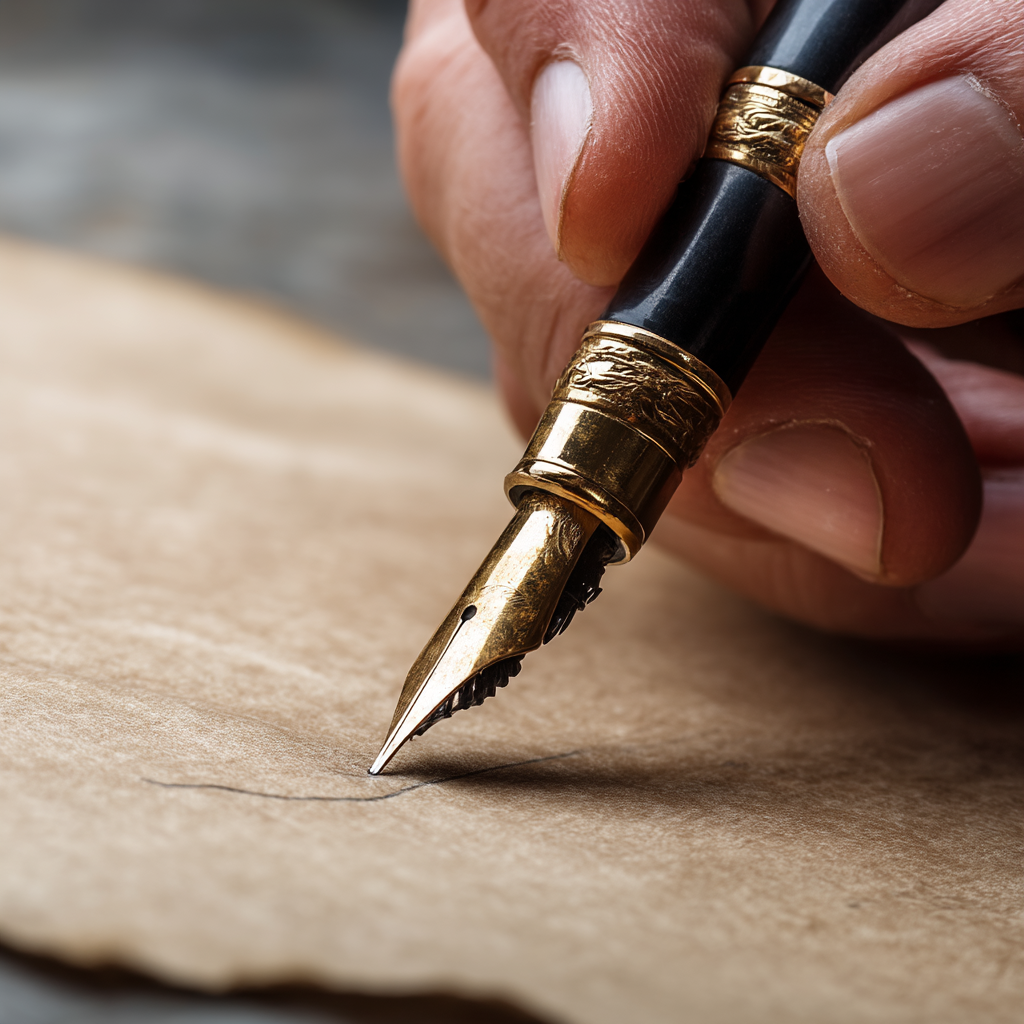
악필 탈출! 하루 10분 글씨 교정 루틴 글씨가 예쁘면 인상이 달라진다고 하잖아요? 그래서 많은 분들이 글씨 교정에 관심을 가지지만, 막상 시작하려면 막막한 경우가 많아요. ‘손이 굳어서 안 돼요’ 혹은 ‘시간이 없어요’라는 고민도 자주 들리죠. 그래서 준비했어요. 하루 딱 10분! 누구나 따라할 수 있는 간단한 글씨 교정 루틴을 공개할게요 😊
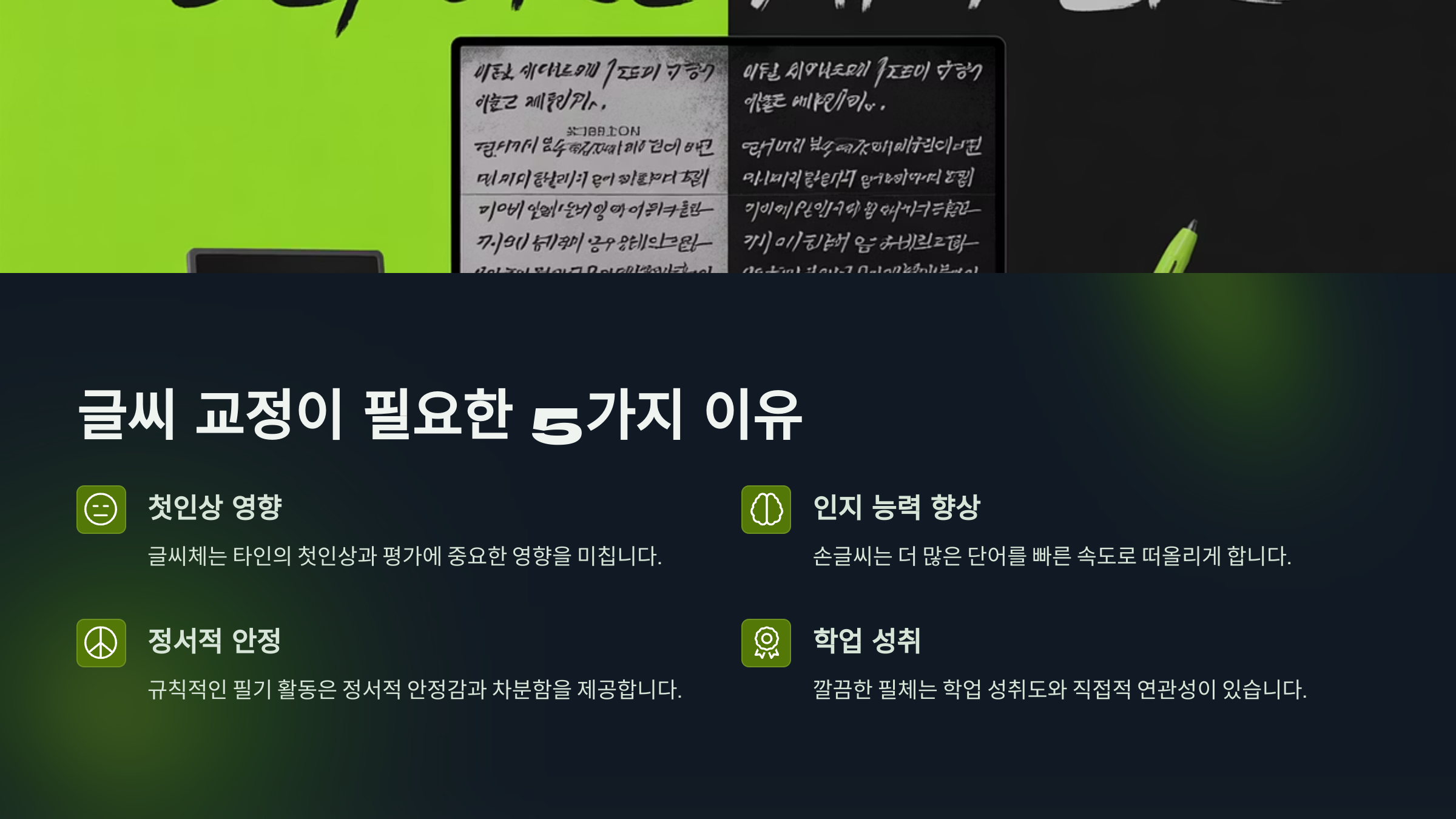
글씨 교정이 필요한 5가지 이유 이 루틴은 단순히 예쁘게 쓰는 법을 넘어, 손의 움직임과 감각을 되살리는 데 초점을 맞췄어요. 필압, 획의 시작과 끝, 자간, 행간 등 기본부터 차근차근 익힐 수 있도록 구성되어 있답니다. 매일 10분만 투자하면 악필에서 벗어나는 건 물론, 자신감도 쑥쑥 자라나게 될 거예요!
🧠 글씨 교정의 필요성과 심리
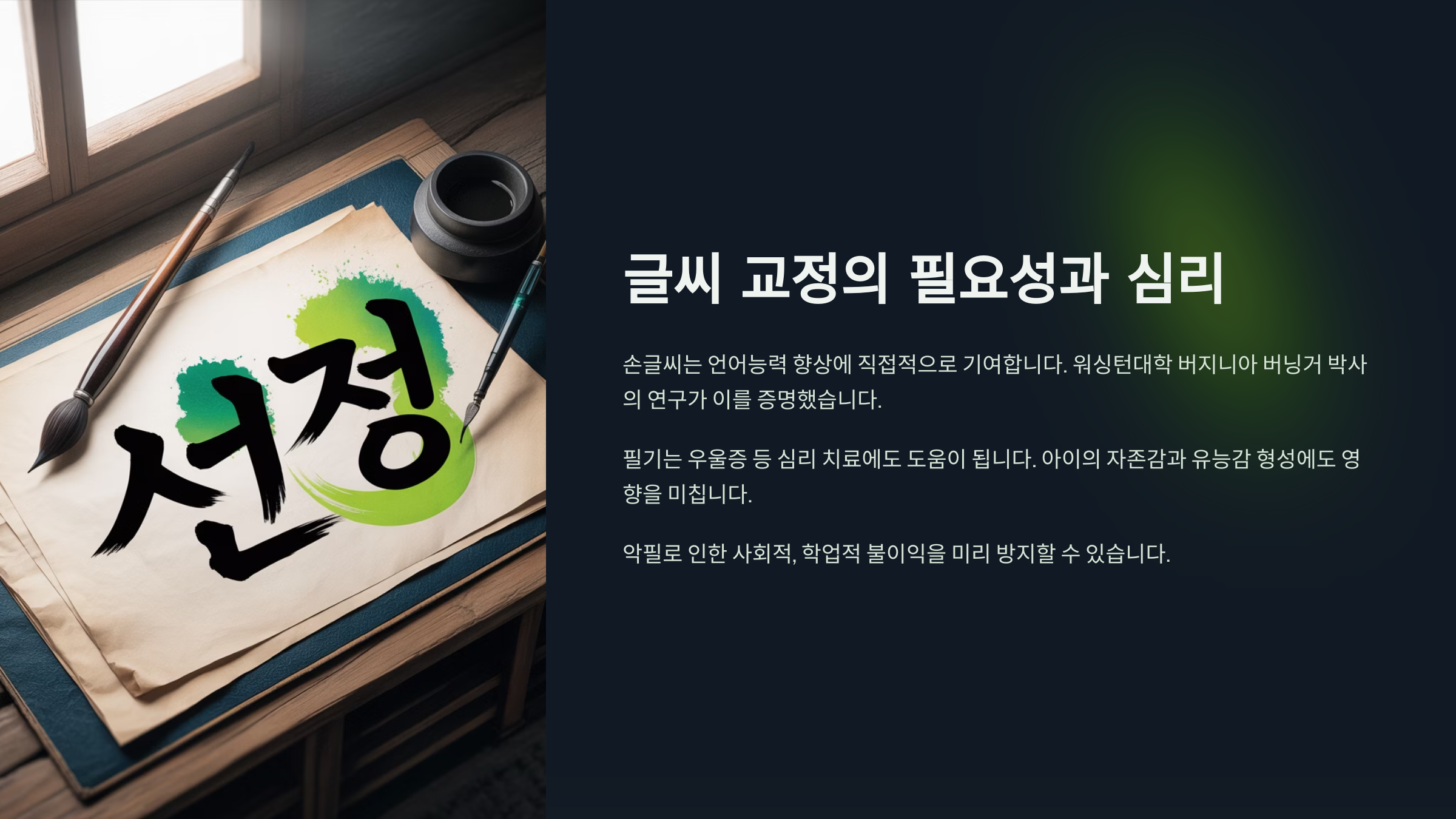
글씨 교정의 필요성과 심리
글씨가 곧 사람의 첫인상이라는 말, 들어본 적 있죠? 특히 메모나 카드, 신청서, 수기 문서처럼 손글씨가 여전히 필요한 상황에선 그 사람의 이미지까지 좌우하곤 해요. 글씨가 삐뚤빼뚤하거나 일관성이 없으면 부주의하거나 급해 보이는 인상을 줄 수 있어요.심리학적으로도 악필은 자신감 부족이나 긴장, 스트레스와 연결되는 경우가 많대요. 반대로 글씨가 또박또박해지면 자신감도 덩달아 높아지고, 집중력까지 향상된다는 연구 결과도 있답니다. 글씨를 바꾸면 생각과 감정까지 긍정적으로 바뀌는 셈이에요 😊
‘나는 원래 악필이야’라고 단정 짓기보단, 의식적인 훈련을 통해 누구나 글씨체를 바꿀 수 있어요. 제어된 반복을 통해 근육 기억을 되살리는 게 핵심이랍니다. 일상 속 작은 실천이 큰 변화를 만들어주는 거예요!
내가 생각했을 때, 글씨는 단순히 시각적인 결과물이 아니라, 나 자신을 표현하는 방식 중 하나라고 느껴져요. 그렇기 때문에 내 글씨가 나를 더 잘 보여줄 수 있도록 노력하는 건 꽤 의미 있는 일인 것 같아요 🖋
📊 글씨 교정이 심리에 미치는 영향
영역 변화 설명 자신감 상승 글씨체 개선은 자신에 대한 믿음을 높여줘요. 집중력 향상 획에 집중하며 쓰는 과정이 집중력을 키워줘요. 자기표현 강화 또박또박한 글씨는 자기 표현력에 영향을 줘요. 손글씨는 그 사람의 내면을 드러내는 도구이기도 해요. 같은 문장이라도 누가 쓰느냐에 따라 전혀 다른 느낌을 주니까요. 글씨를 바꾸려는 마음가짐은 나를 새롭게 재정비하는 첫걸음이 될 수 있어요!
그런 이유로 요즘엔 ‘필사’나 ‘펜글씨 연습’이 감정 조절을 위한 힐링 활동으로도 주목받고 있어요. 집중해서 손글씨를 쓰는 동안 마음이 안정되고 불안도 줄어든다고 하니, 일석이조의 효과를 누릴 수 있답니다.
물론 처음엔 어색할 수 있어요. 하지만 계속 쓰다 보면 손에 익고, 어느 순간부터는 손이 먼저 반응하게 된답니다. 꾸준함이 가장 강력한 무기예요 💪
글씨 교정이 단순한 연습을 넘어서, 자기 성찰의 과정이자 긍정적인 루틴이 될 수 있다는 점, 꼭 기억해보세요. 멋진 손글씨는 결국 내면의 자신감에서부터 시작돼요!
⏰ 하루 10분 루틴의 핵심 원칙
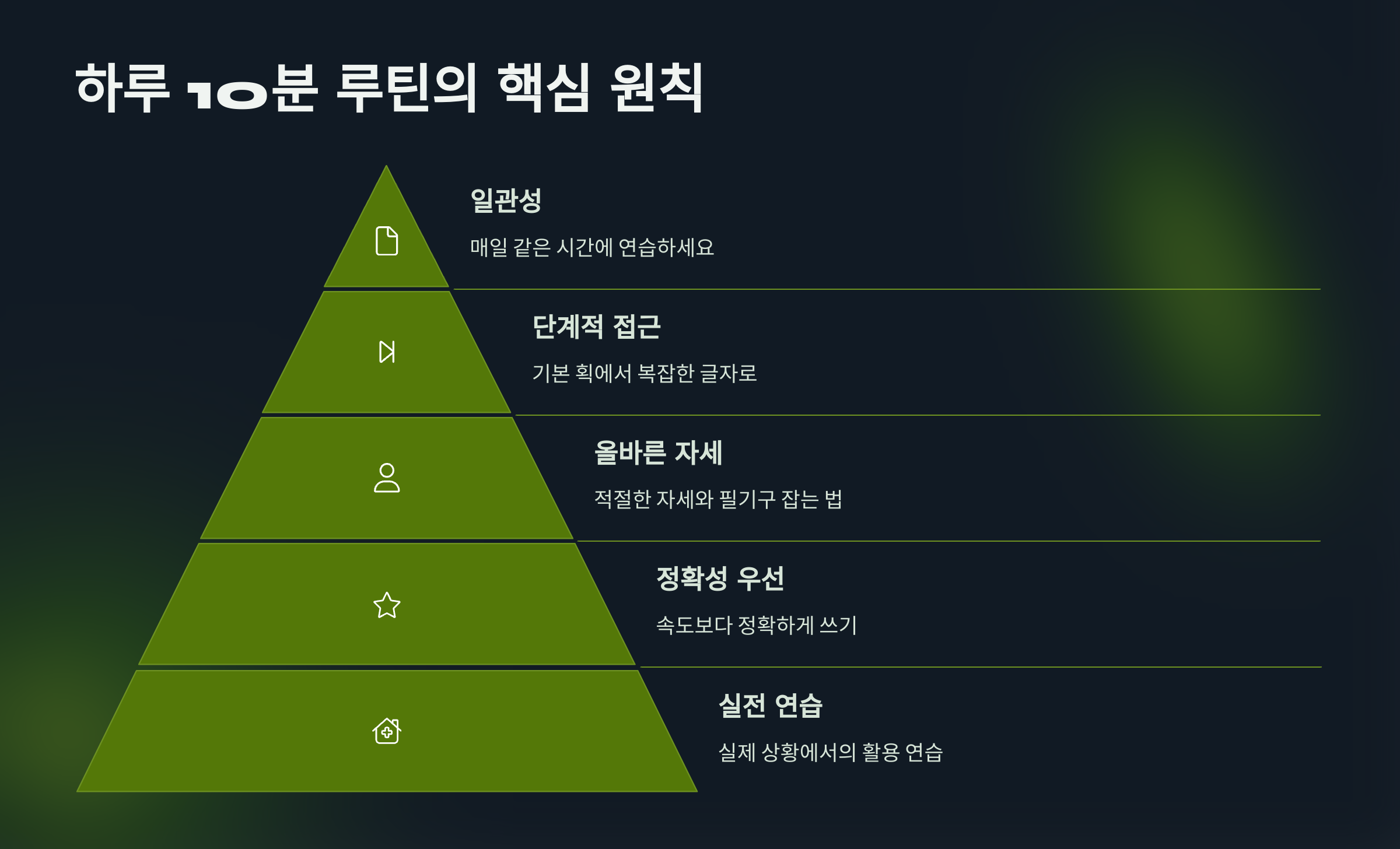
하루 10분 루틴의 핵심 원칙 글씨 교정에 필요한 시간은 사실 생각보다 짧아요. 하루에 단 10분만 투자해도 손의 움직임과 근육 기억을 충분히 자극할 수 있답니다. 중요한 건 그 시간을 얼마나 ‘집중해서’ 사용하느냐에 달려 있어요.
핵심은 ‘짧고 자주’. 한 번에 오래 쓰는 것보다, 매일 꾸준히 조금씩 연습하는 게 훨씬 효과적이에요. 뇌와 손의 연결을 지속적으로 훈련해야 진짜 내 글씨가 되니까요. 물 흐르듯 반복하는 것이 관건이랍니다.
또 하나 중요한 원칙은 ‘올바른 자세’. 글씨는 손끝에서 나오지만, 전체적인 자세가 흐트러지면 손에 힘이 제대로 전달되지 않아요. 바른 자세와 편안한 필기 환경을 만들어주는 것부터 시작해보세요 😊
연습할 때는 글자 하나하나에 ‘의식’을 담는 것이 좋아요. 아무 생각 없이 휘갈기기보다는, 획의 시작과 끝을 의식하면서 쓰면 훨씬 빠르게 개선된답니다. 이 과정을 통해 손글씨에 정성이 담기게 되어요.
🪄 루틴 성공을 위한 5가지 키포인트
원칙 설명 매일 10분 지속성 있는 반복이 가장 중요해요. 바른 자세 등은 세우고, 손목에 무리가 가지 않도록 해요. 획 연습 일직선, 곡선, 점 등 기본 획 연습이 핵심이에요. 의식적인 쓰기 생각하며 천천히 쓰는 게 훨씬 효과적이에요. 기록과 비교 진행 상황을 기록하면 동기부여가 생겨요. 이 다섯 가지 원칙만 잘 지켜도, 놀라울 정도로 글씨가 달라진답니다. 중요한 건 ‘완벽하게’가 아니라 ‘꾸준하게’라는 점! 너무 부담 갖지 말고 즐기는 마음으로 시작해보세요 😄
또한, 무리해서 필사량을 늘리기보다는 짧은 문장을 반복하는 것이 더 효과적이에요. 특히 익숙한 문장을 골라 감정을 담아 쓰면 글씨에 힘이 실리거든요.
자기 전에 10분, 혹은 아침 루틴에 포함시키는 것도 추천해요. 하루의 시작과 끝에 글씨를 쓰면 뇌와 손이 자연스럽게 리듬을 타게 된답니다.
이제 루틴의 핵심을 알았다면, 실제로 어떻게 구성하는지 궁금하시죠? 다음 섹션에서 바로 소개해드릴게요 ✨
📘 실제 루틴 구성 방법
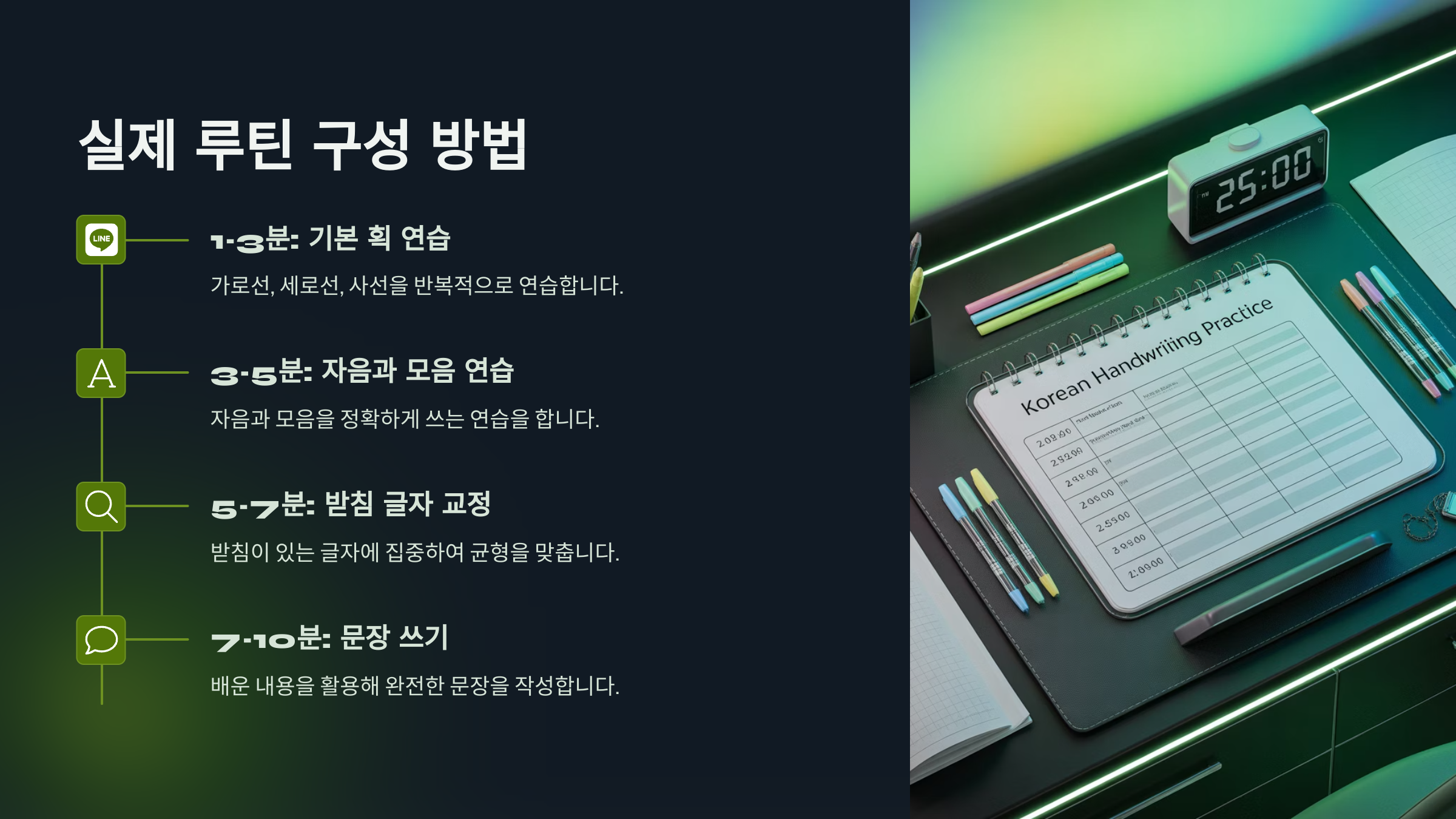
실제 루틴 구성 방법
실제 글씨 교정 루틴은 간단하지만 체계적으로 짜는 것이 중요해요. 여기선 아침 10분 루틴을 기준으로 설명드릴게요. 이 루틴은 초보자도 쉽게 따라할 수 있도록 설계되어 있어요.1분 준비 – 자세 잡기 & 필기도구 정렬
2분 기초 획 연습 – 세로선, 가로선, 점찍기
3분 단어 반복 – ‘감사’, ‘행복’, ‘기쁨’ 등 감성 단어 쓰기
3분 문장 연습 – 좋아하는 시구나 명언 필사
1분 체크 – 오늘 글씨에서 달라진 점 보기이렇게 구성하면 단순한 연습이 아닌, 감정과 마음까지 담긴 루틴이 돼요. 좋아하는 글귀를 반복해 쓰다 보면 글씨와 함께 하루의 감정도 정돈되는 느낌을 받을 수 있죠 ✨
매일 같은 문장을 쓰는 것도 좋지만, 주제를 바꿔보는 것도 좋아요. 예를 들어 월요일은 ‘희망’, 화요일은 ‘도전’ 같은 식으로 테마를 바꾸면 루틴이 지루해지지 않아요 😊
📑 루틴 구성 예시표
시간 활동 목적 1분 자세 정렬 & 준비 몸과 마음 집중하기 2분 기초 획 쓰기 선의 균형 & 필압 훈련 3분 단어 필사 단어 형태 익히기 3분 문장 필사 글씨 흐름 익히기 1분 글씨 피드백 자기 점검 & 변화 체감 이 루틴은 아침이나 점심, 자기 전 등 하루 중 어느 시간에 해도 효과는 같아요. 중요한 건 같은 시간, 같은 장소에서 반복하는 습관을 들이는 거예요. 습관이 되면 손이 먼저 반응하게 될 거예요 ✍
특히 루틴 중 마지막 ‘피드백’ 단계가 정말 중요해요. 작은 변화라도 놓치지 않고 적어보면 꾸준히 쓰고 싶은 마음이 생기거든요. 변화가 눈에 보일 때 성취감도 덩달아 커지니까요!
그럼 다음 박스에서는 글씨를 교정하는 데 도움이 되는 ‘필기 도구’에 대해 알아볼게요! 도구 하나만 바꿔도 결과가 확 달라진답니다 🖊
🖋 도움이 되는 필기 도구들
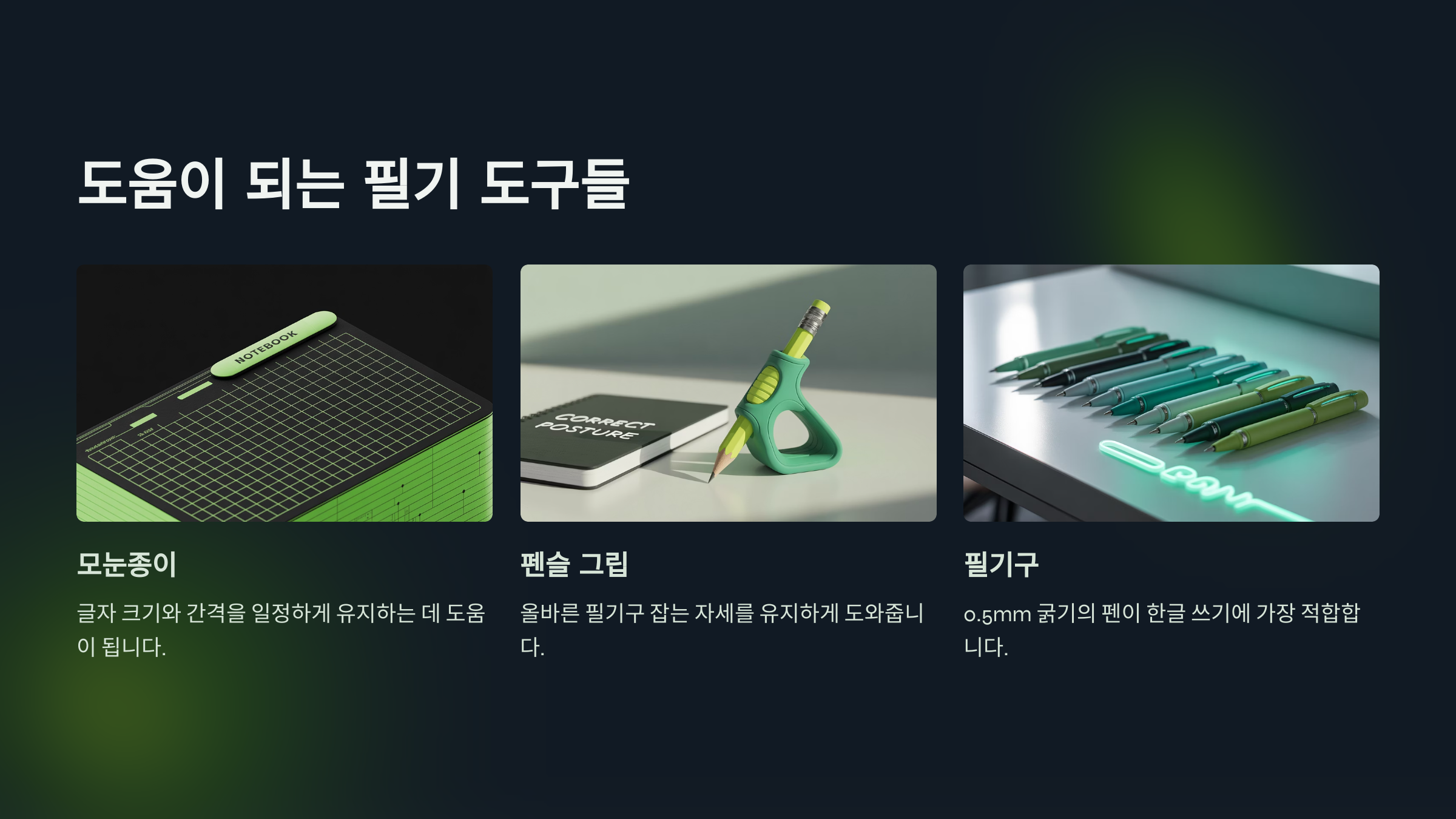
도움이 되는 필기 도구들
글씨 교정에 있어 ‘무엇으로 쓰느냐’는 생각보다 중요한 요소예요. 필기 도구가 손에 잘 맞아야 편안하게 쓸 수 있고, 그만큼 획도 안정적으로 나와요. 손에 부담이 적으면서도 제어하기 쉬운 도구를 고르는 게 핵심이죠!가장 추천되는 건 젤펜이나 저점도 볼펜이에요. 부드럽게 써지면서도 필압 조절이 쉬워서 획을 안정적으로 그릴 수 있답니다. 필기감도 좋고 번짐도 적어서 초보자에게 안성맞춤이에요.
연습 초반에는 연필을 사용하는 것도 좋아요. 특히 2B 정도의 부드러운 연필은 손의 떨림을 잡아주고 획의 흐름을 확인하기 쉬워요. 다만 너무 미끄럽거나 번지는 펜은 피하는 것이 좋아요!
노트 선택도 중요해요. 줄 간이 너무 촘촘하면 자간 조절이 어렵고, 너무 넓으면 글자 크기가 불안정해지죠. 6mm~7mm 간격의 라인노트가 가장 이상적이에요. 그리드 노트도 자형 익히기에 효과적이랍니다 📒
🛠 추천 필기 도구 비교표
도구 장점 단점 추천 여부 젤펜 부드러운 필기감, 명확한 획 잉크 양 많으면 번짐 👍 적극 추천 저점도 볼펜 정확한 제어 가능 힘이 들어가면 끊김 발생 ⭕ 추천 2B 연필 획의 연습에 최적 지워질 수 있음 🔄 초보자 추천 글씨 교정은 도구에 따라 흥미와 지속력도 좌우될 수 있어요. 나에게 맞는 펜 하나만 찾아도 쓰는 재미가 생기고, 루틴이 자연스럽게 이어진답니다 😄
도구를 고를 때는 문구점에서 실제로 테스트해보는 것도 추천해요. 손에 맞는 필기감은 사람마다 다르기 때문에 직접 써보는 게 제일 정확하죠!
그럼, 다음 섹션에서는 글씨를 교정하면서 흔히 저지르는 실수와 그 해결법을 알려드릴게요! 실수도 과정의 일부니까 걱정 말고 함께 살펴봐요 🔍
❌ 교정 시 흔한 실수와 해결법
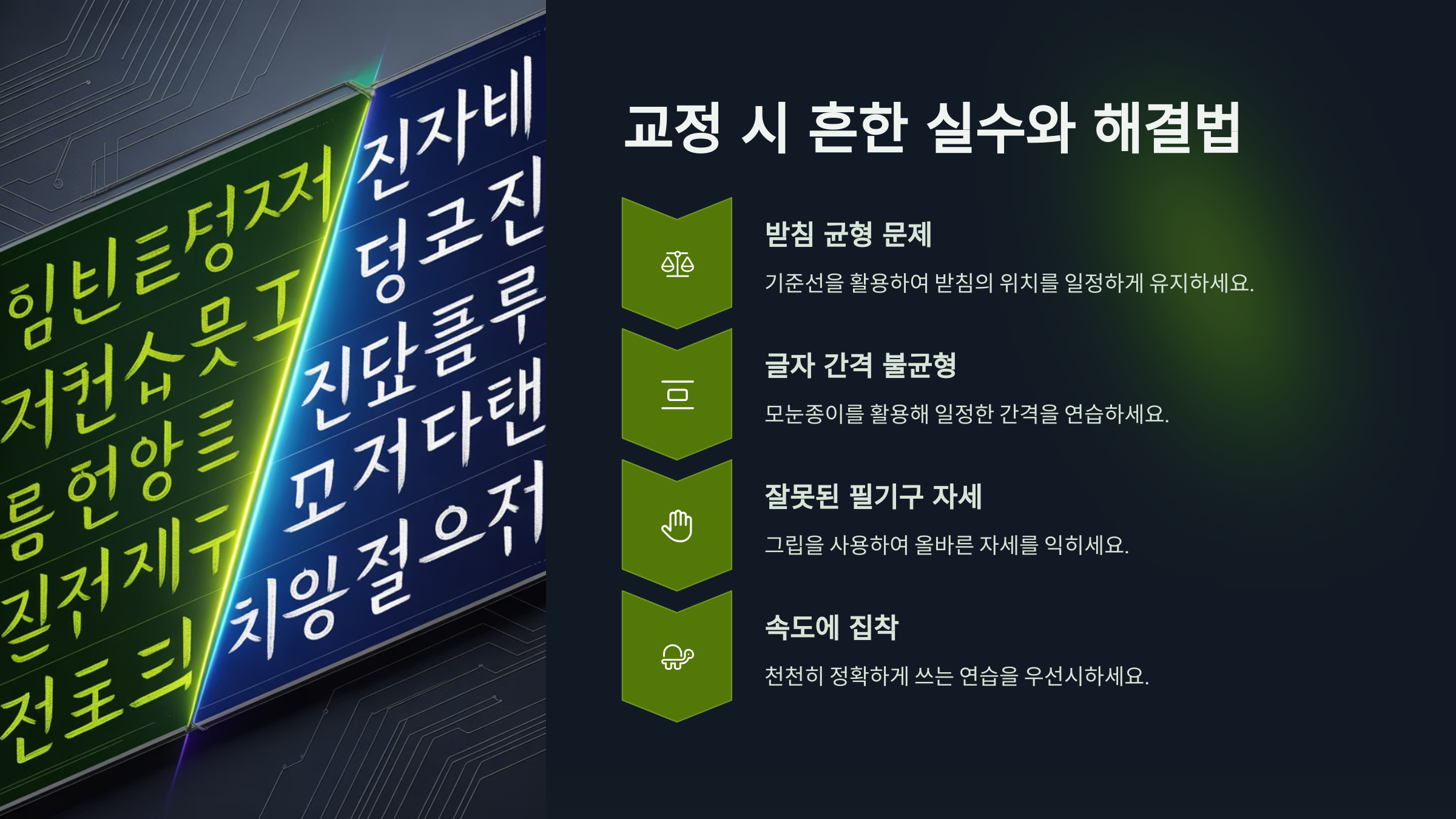
교정 시 흔한 실수와 해결법 글씨 교정은 반복적이고 지루할 수 있는 작업이지만, 실수도 교정 과정의 일부랍니다. 처음에는 흔히 저지르는 실수들이 있어요. 그런 실수들을 파악하고 고쳐나가는 게 중요해요!
첫 번째 실수는 ‘급하게 쓰는 것’이에요. 글씨는 시간과 마음을 들여서 써야 예쁘게 나옵니다. 서둘러 쓴 글씨는 획이 일관되지 않고, 형태가 흐트러지기 일쑤죠. 글씨를 쓸 때는 천천히, 신중하게 쓰는 것이 필요해요.
두 번째는 ‘자세가 불안정한 것’이에요. 책상에 앉아서 허리를 구부리고 쓰면 팔꿈치가 떠서 필압이 고르지 않아요. 바른 자세를 잡는 게 필기에서 중요한 포인트랍니다. 책상에 팔꿈치를 고정하고, 손목을 부드럽게 유지해 보세요.
세 번째 실수는 ‘글씨의 크기와 자간을 일정하게 유지하지 않는 것’이에요. 자간이 너무 좁거나 넓으면 글씨가 어지럽게 보일 수 있어요. 이를 해결하려면 ‘눈에 보이는 것보다 조금 더 넓게 쓰는’ 연습을 해보세요. 자간을 의식적으로 조정하면서 글씨를 써보면 개선된답니다 ✍
🧐 교정 시 자주 하는 실수 & 해결 방법
실수 해결법 급하게 쓰기 천천히, 신중하게 한 획씩 그리기 자세 불안정 팔꿈치 고정, 손목을 부드럽게 유지 자간 불규칙 의식적으로 자간을 일정하게 맞추기 이 실수들은 누구나 처음에 겪는 것들이에요. 하지만 이를 인식하고 수정하면 금방 글씨가 예뻐지고, 교정도 쉬워질 거예요! 조금만 인내심을 가지고 계속 연습하다 보면 점점 글씨에 자신감이 생길 거예요 😊
글씨를 고칠 때 가장 중요한 건 바로 ‘꾸준함’이에요. 하루 10분 루틴을 지속하면 점점 눈에 띄게 개선될 거랍니다. 실수도 반복하면서 고쳐가니까요! 글씨 교정은 한 번에 완벽하게 되는 게 아니라, 점진적으로 나아가는 과정이에요.
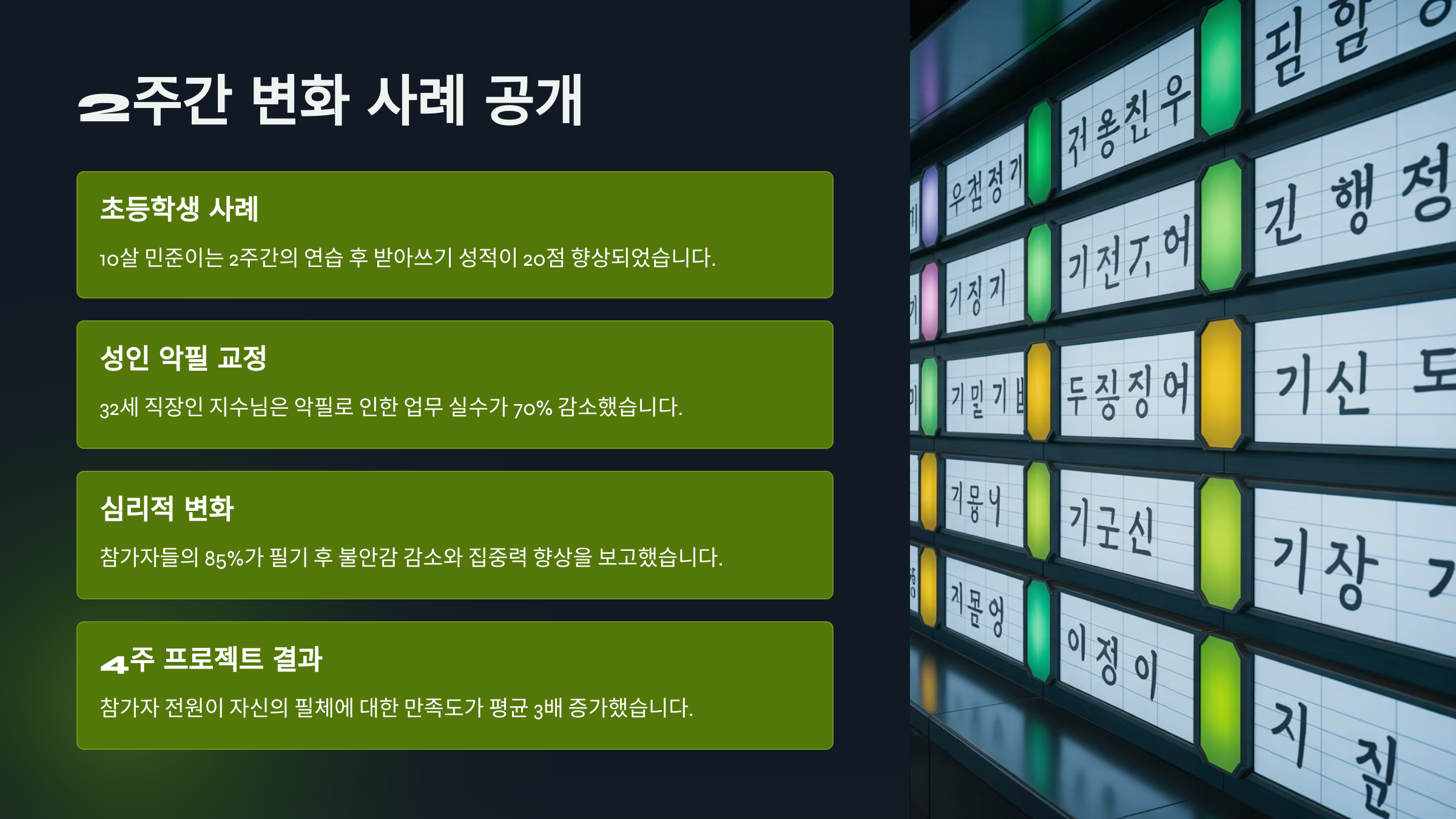
2주간 변화 사례 공개 📈 2주간 변화 사례 공개
자, 그럼 이제 2주간의 변화 과정을 공개할게요! 하루 10분씩만 투자해도 정말 많은 변화가 있어요. 아래 사례를 통해 변화 과정을 함께 살펴보세요.
첫 주에는 손의 움직임을 정확히 조절하는 데 집중했어요. 획을 일정하게 만들고, 글자 크기와 자간을 맞추기 위해 신경을 썼죠. 그 결과, 글씨가 조금 더 일정해졌고, 일관된 느낌이 들었어요. 두 번째 주에는 자세를 더욱 신경 써서 글씨의 안정감을 확실히 느낄 수 있었답니다.
2주 후에는 무엇보다 ‘자신감’을 느낄 수 있었어요. 예전엔 손글씨가 조금 부끄럽고 불안정한 느낌이었는데, 이제는 깔끔하고 안정적인 글씨를 쓸 수 있게 됐어요. 꾸준히 연습하다 보니 손이 자연스럽게 움직여지더라고요!
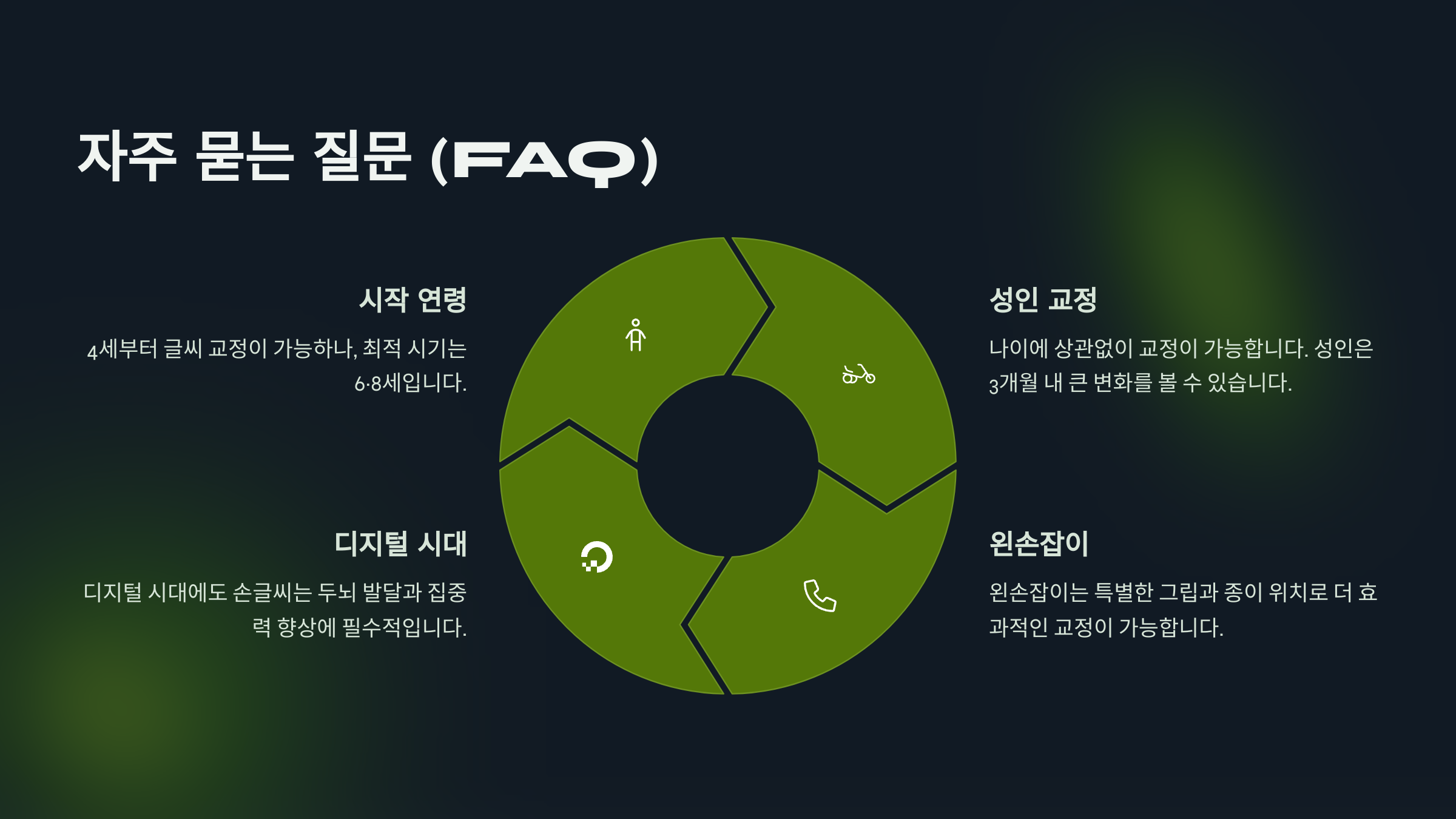
Q1. 글씨 교정은 정말 효과가 있나요?A1. 네, 꾸준히 연습하면 확실히 효과가 있어요. 글씨 교정은 손의 근육 기억을 개선하고, 자신감을 높여줍니다. 특히 2주 정도 꾸준히 하다 보면 눈에 띄는 변화를 느낄 수 있어요!
Q2. 하루 10분만 하면 충분한가요?
A2. 네, 하루 10분이라도 꾸준히 한다면 충분히 효과를 볼 수 있어요. 중요한 건 시간을 정해 놓고 매일 꾸준히 연습하는 것이랍니다.
Q3. 글씨 교정을 할 때 어떤 도구를 써야 하나요?
A3. 젤펜이나 저점도 볼펜이 추천돼요. 필기감이 부드러워서 제어가 쉬운 도구를 사용하면 글씨가 훨씬 안정적으로 써져요.
Q4. 글씨가 예쁘지 않으면 어떻게 해야 하나요?
A4. 처음에는 누구나 글씨가 마음대로 되지 않아요. 중요한 건 꾸준히 연습하면서 조금씩 개선하는 거예요. 너무 빨리 포기하지 말고, 한 걸음씩 나아가면 좋아요!
Q5. 교정할 때 자주 하는 실수가 무엇인가요?
A5. 급하게 쓰거나 자세가 불안정한 경우가 많아요. 이럴 때는 천천히 글씨를 써보거나, 바른 자세를 유지하며 필기하는 것이 좋아요.
Q6. 글씨 교정을 할 때 필기구는 계속 바꿔야 하나요?
A6. 아니요, 일관되게 사용하는 것이 중요해요. 일단 자신에게 맞는 필기구를 찾은 후에는 그 도구로 꾸준히 연습하는 것이 더 효과적이에요.
Q7. 글씨를 개선하면 심리적으로 변화가 있나요?
A7. 네, 글씨를 개선하면 자신감이 상승하고, 집중력도 향상돼요. 글씨는 단순한 외적인 결과물이 아니라 내면의 변화를 반영하는 중요한 요소랍니다!
Q8. 얼마나 시간이 지나야 글씨가 눈에 띄게 좋아질까요?
A8. 보통 2주 정도 꾸준히 연습하면 눈에 띄게 달라진 글씨를 볼 수 있어요. 중요한 건 반복적인 연습과 피드백이랍니다!
이제 여러분도 하루 10분의 글씨 교정 루틴으로 멋진 필체를 만들어 보세요! 꾸준함과 집중이 중요하니까요. 😊